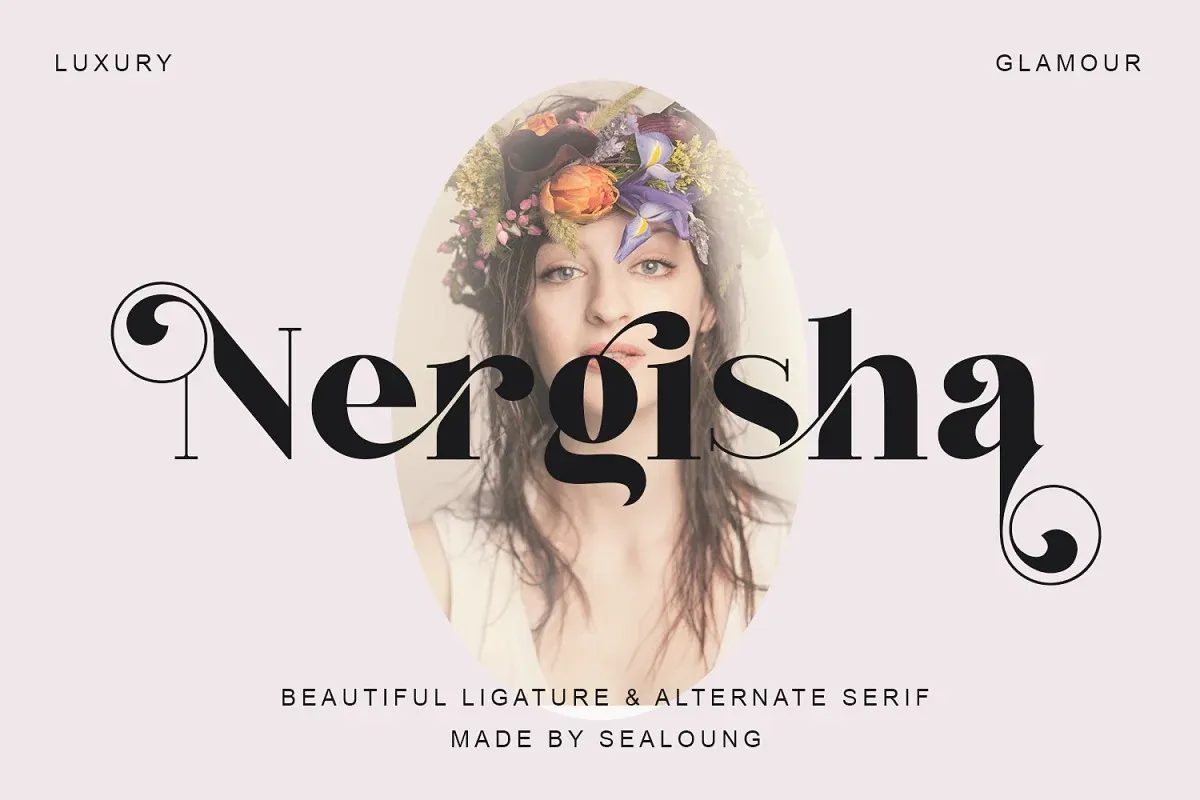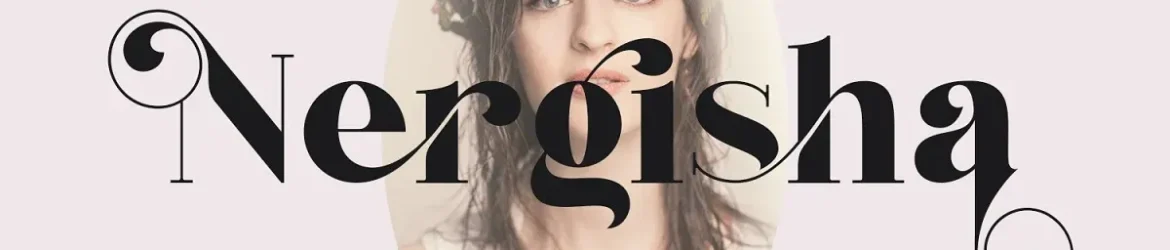
A Nergisha Font é uma elegante serif moderna que traz um toque único e luxuoso ao seu design. Cada caractere desta tipografia foi projetado com cuidado para oferecer um equilíbrio perfeito entre clássico e contemporâneo, o que a torna ideal para diversos tipos de trabalhos gráficos. Suas alternativas variadas de 70+ permitem criar formas fluidas e bonitas em apenas segundos, tornando-a uma fonte ótima para projetos de marca, identidade visual, design de casamentos, postagens na mídia social, anúncios e embalagens de produto. A Nergisha é perfeitamente apropriada para uso em produtos digitais e físicos, incluindo etiquetas, fotografias, marcadores de água, convites e materiais de decoração, criando designs com alta legibilidade e uma aparência luxiosa que vai do papel ao digital.